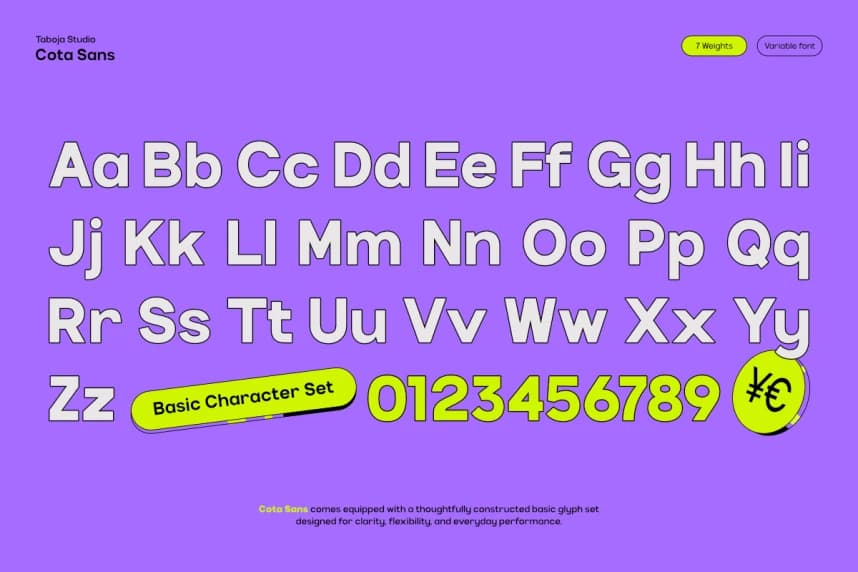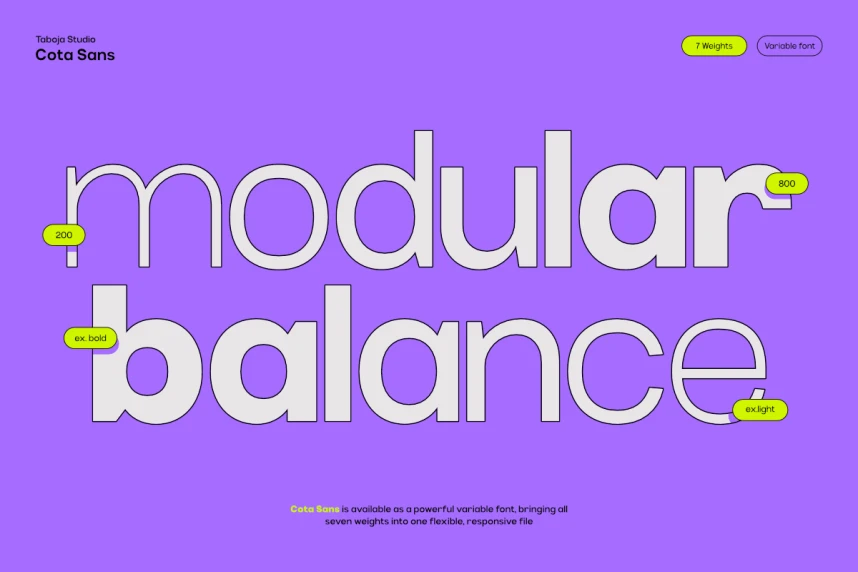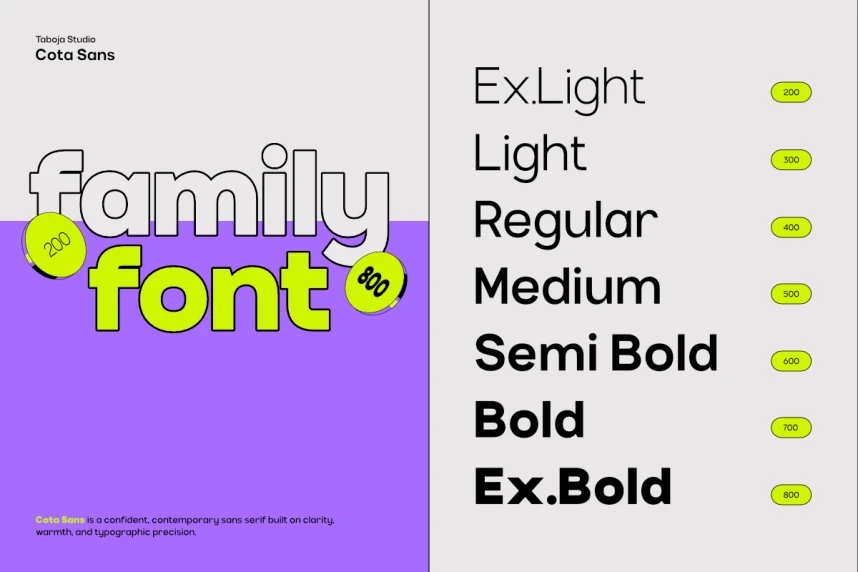
TBJ Cota Sans Yazı Tipi
TBJ Cota Sans Font bağırmak için yaratılmadı. Net ve kendinden emin, amaca yönelik bir şekilde konuşması için tasarlandı. Görsel gürültünün dikkati çekmek için yarıştığı bir dünyada, Cota Sans sessiz bir düzen sistemi olarak öne çıkar.
TBJ Cota Sans Yazı tipi bağırmak için tasarlanmadı. Açık, kendinden emin ve amaçlı konuşacak şekilde tasarlandı. Görsel gürültünün dikkat çekmeye çalıştığı bir dünyada, Cota Sans sessiz bir düzen sistemi olarak durur.